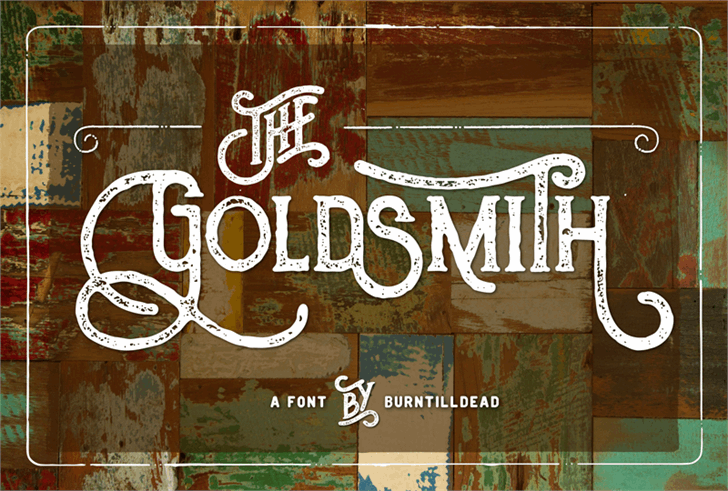
A fonte ‘The Goldsmith Vintage’ é uma criação cuidadosamente elaborada pelo designer Hamilton. Inspirada na serif moderna feita à mão com riqueza e consistência, essa fonte apresenta cada característica de forma única e detalhada, evocando a elegância de um tipo clássico em revestimento de metal. O estilo vintage presente nesta fonte traz uma atmosfera sofisticada e retro que certamente se encaixa perfeitamente para design gráfico moderno ou qualquer projeto que desejasse incorporar este brilho nostálgico na sua identidade visual. Com seu formato de exibição sólido, ‘The Goldsmith Vintage’ é uma fonte ideal tanto para títulos quanto para conteúdo em pequeno tamanho, tornando-se um complemento perfeito para qualquer design que valorize a elegância e o glamour do passado modernizado.